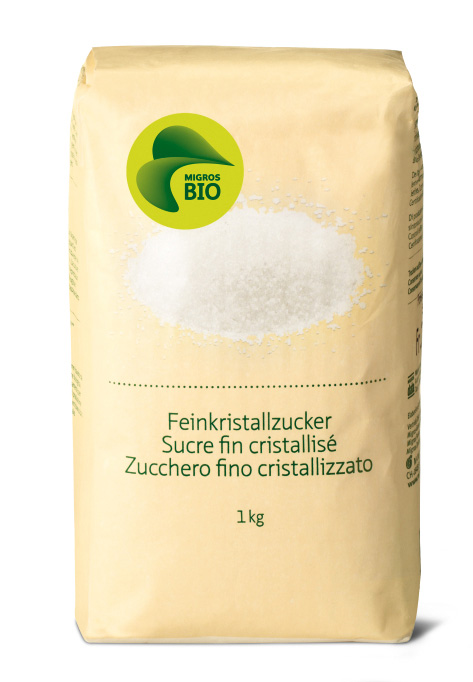
Schweizer Lebensmittelkunden, ihr habt es wirklich gut. Die Bio-Produkte von Migros sind nicht nur typografisch eine Augenweide (bitte mal links zwecks Vergrößerung auf die Zuckerpackung klicken) … nein, das Handelsunternehmen zeigt auch, wie man ein Bio-Siegel selbstbewusst entwerfen lässt und genauso selbstbewusst einführt – ohne Kundenabstimung, wahrscheinlich auch ohne monatelange Pitches (Agentur: Schneiter Meier Külling).
Migros ist mit einem Jahresumsatz von 25 Mrd. CHF nicht nur der größte Einzelhändler in der Schweiz, sondern in vielen Bereichen auch sein eigener Hersteller und Lieferant. In den Anfangsjahren war das eigene Sortiment lediglich die Reaktion auf politisch motivierte Lieferverweigerung, später wurde es zum Wettbewerbsvorteil. Erst in jüngerer Zeit hielten Markenprodukte wieder verstärkt Einzug in die Migros-Läden.
Im vergangenen Jahr verzeichnete Migros bei den Bioprodukten ein Umsatzwachstum von sieben Prozent. Die gestiegene Nachfrage sorgte für Einsparungen und bietet nun Spielraum für günstigere Preise. Ab heute senkt die Handelskette die Preise ihres Biosortiments um durchschnittlich 5 Prozent. Änderungen gibt es auch bei der Verpackung und beim Logo. Der neue Auftritt diene den Kunden als Orientierungshilfe, teilt Migros gegenüber der Presse mit. Zur Zeit führe man über 1000 Bioprodukte. Das Sortiment soll bis Ende 2010 laufend erweitert werden. »Wir lancieren in allen Bereichen neue und innovative Artikel. Schwerpunkt sind die Sortimente Brotwaren, Molkereiartikel, Fleischwaren und Tiefkühlprodukte«, erklärt Marketingleiter Oskar Sager.
Die neuen Verpackungen gefallen mir wirklich gut. Soweit ich das Sortiment gerade überflogen habe, gibt es auch keine größeren Ausreißer.
Erste Sahne!
Mutig finde ich nicht nur ein eigenes Bio-Siegel einzuführen, sondern auch so eine reduzierte Verpackungsgestaltung zu wagen. Gefällt mir ausgesprochen gut!
Wertschätzung von Design!
Schön! Migros hatte schon immer gute Verpackungen. Wenn jetzt alle so eine reduzierte Gestaltung hätten, dann wäre unsere Einkaufslandschaft doch recht langweilig. Außerdem – wie würde ich dann mein Junkfood finden? Die Firma Egle im bayerischen macht übrigens auch sehr schöne reduzierte Verpackungen! http://wilhelm-egle.de/ Aloha Gert Wiescher
Ich finde auch: eine ausgesprochen feine Sache! Die angeführten Beispiele von Herrn Wiescher wirken roh und veraltet dagegen. Und noch rein hypothetisch: Minimalistisches Design überall hiesse ja noch nicht *dasselbe* Konzept überall. Aber ich mache mir auch keine Sorgen: Hässliche Produkte wird es immer geben, auch in der Schweiz!
Mit dem »Egle«, da haben sie recht Herr Paul S. die haben das offensichtlich an die Gestaltung von »Marks und Spencer« angelehnt und nicht richtig hinbekommen. Ich finde nur, man sollte nicht alles so minimalistisch sehen, wird sonst stocklangweilig. Aloha Gert Wiescher
sehr schön, sehr schön
Das Logo ist nett, aber die Gesamtgestaltung finde ich hässlich.
ich mag die zurückhaltende gestaltung. insgesamt ist die gestaltung der packungen von eigenmarken bei migros um längen besser als die der konkurenz – siehe coop prix garantie von coop, dem zweitgrössten detailhändler der schweiz. gerade auch im gegensatz zur billiglinie von migros, migros budget, die designmässig spezifisch auf billig getrimmt ist.
Die Gestaltung sieht schlüssig aus.
Allerdings frage ich mich, wer sich hier von wem hat inspirieren lassen: http://www.behance.net/Gallery/Corporate-and-brand-identity-Amova/253342
Schaut euch mal die Bioverpackung der Alpenkräuter Tee flasche an. Da fällt das Design total zusammen.
Nichts als liebe für den Migros, aber so innovativ finde ich das Design nicht. Schön, aber riecht nach Neo-Helvetischem Konservatismus ;). Die Schweiz hat scheinbar mühe, aus den bekannten Bahnen zu brechen. Kein Wunder fragt die Swisscom Engländer, um Ihre CID zu gestalten.
Mir gefallen die Bio-Produkte vom Konkurrenten Coop sehr viel besser. Sehr schöne Typographie (das ist die PTL Notes Soft, glaube ich), schaut mal hier: Link
da ich grad am Wochenende in Basel war, ist der Eindruck noch sehr frisch. Ich liebe den ‘Neo-Helvetischem Konservatismus’. Ob in Design oder Architektur. Der Schock kommt, wenn man aus dem beschaulichen Riehen nach Lörrach kommt.
Mir gefällts und ich kaufs auch. Die Migros hat schon immer Wert gelegt auf gutes Design. Natürlich geht so ein Konzept nicht immer überall auf, gerade bei den neuen M-Classic Produkten http://www.migros.ch/DE/Supermarkt/Markenwelt/M_Classic/Seiten/M_Classic.aspx , die auch ziemlich neu gestaltet wurden, aber im grossen und ganzen mag ichs.
Die alten Verpackungsdesignklassiker der Migros gibts auch als Kleider: http://www.m-stars.ch/ natürlich ist es für jemanden der nicht damit aufgewachsen ist mässig interessant aber evt ein klick wert…
hier noch ein Zuckerpackdesign: http://lovelypackage.com/student-work-pamela-rounis/
wie jetzt? landliebe ist mit eigenem biosiegel böse, migros aber gut? mir scheint die community hier lässt sich mit guter typo bestechen ;-)
@cd-rw – der Einwand ist im Prinzip berechtigt. Allerdings hatte die Migros schon vorher ein eigenes Bio-Siegel, weil man sich nicht in allen Punkten an die strengeren Richtlinien der Bio-Suisse (die das offizielle Knospen-Siegel vergeben) hält. Das machen andere Supermarktketten in D und CH ja leider auch so.
Sehr harmonisch und doch ein Hingucker. Gefällt mir super!
Weiss jemand, welche Schrift das ist? Laufschrift der Bioprodukte?